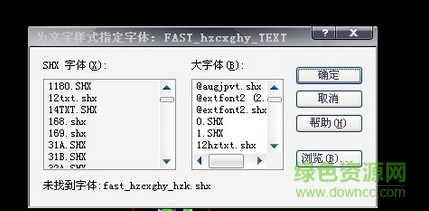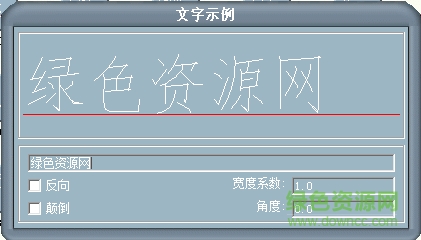
fast_hzcxghy_hzk字體是專門為城鄉(xiāng)建設(shè)規(guī)劃圖紙打造的字體,很多在設(shè)計(jì)城鄉(xiāng)規(guī)劃圖紙時(shí)會(huì)提示指定字體fast_hzcxghy_hzk,以下圖為例,有需要的朋友就來綠色資源網(wǎng)下載吧!
AUTCAD中fast hzcxghy hzk體的字體為大字體而不是圖形,在很多地方都找不到這個(gè)字體,下面的方法很簡(jiǎn)單就能代用,我現(xiàn)在介紹給大家。